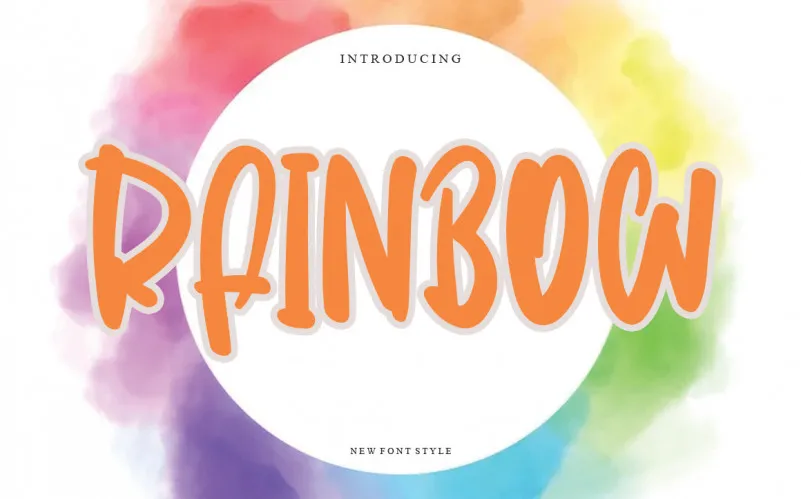
Rainbow Script Font – Download Grátis
A Rainbow Script Font é uma opção perfeita para quem busca adicionar um toque alegre e único a seus projetos digitais. Este script feito à mão é ideal tanto para desenhos relacionados a personagens de quadrinhos, quanto para jogos infantis, mantendo sempre uma sensação relaxada e descontraída. Seja para decorar logotipos ou criar layouts interativos, esta fonte se destaca por sua facilidade em transformar qualquer projeto em algo que brilha com vida e personalidade. Ideal tanto para uso pessoal quanto para aplicações comerciais, a Rainbow Script Font é perfeita para aquelas criações que desejam um ar descontraído e encantador.